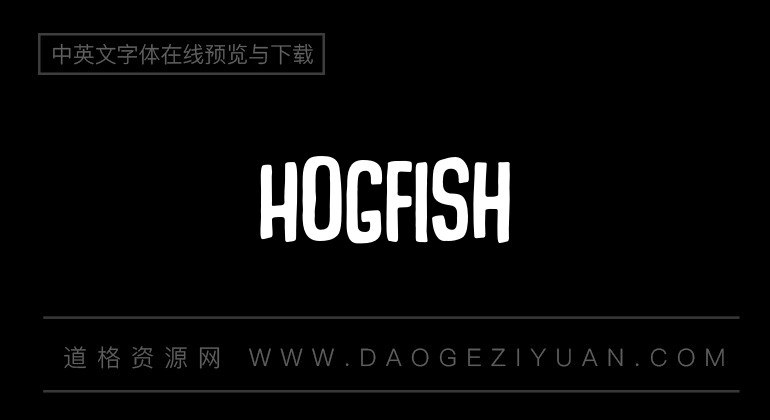
Hogfish
? Hogfish字体是一款英文字体,它的特点是粗体、粗犷、英式风格,适用于多种商业和个人用途,比如标题、广告、标签等等。它的字体设计简洁,更具有表达力,能够更好地传达消息。它的字体颜色经过多次调整,有利于用户在不同环境中更好地阅读文本,并且可以调整字体大小,以适应不同的用户需求。
Hogfish是一款非常不错的手写艺术字体,具有很好的视觉感,适合于文化类的宣传设计、商业类品牌的广告和产品包装设计以及个性化文字排版等较多场景。